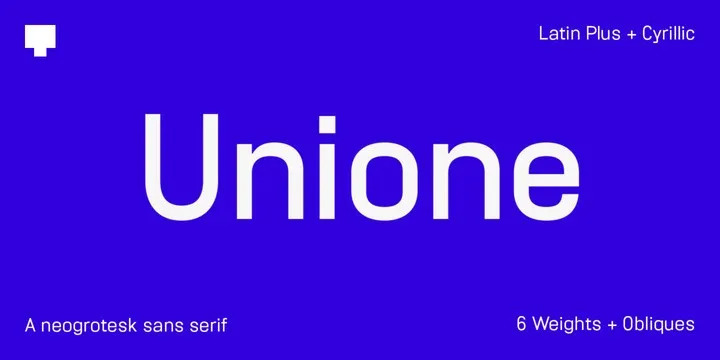
A Befonts está entusiasmada ao apresentar uma nova família de fontes sans-serif moderna. Esta é uma família de tipo sans serif universal – limpa e eterna, perfeita para um leque vasto de necessidades, desde identidades de marcas até design editorial, publicidade e logotipos. A Unione Font foi criada pelo designer TOMO Fonts e apresenta um estilo clean e moderno, com uma pegada geométrica. Esta família de fontes é disponível em seis pesos (agressivo e redondinho) e inclui suas respectivas obliques. Com mais de 28 membros na família, cada tipo possui mais de mil caracteres! Além disso, a Unione Font oferece uma ampla gama de suporte linguístico, incluindo o Latin Plus e Cyrillic. Os interessantes alternados estilísticos da Unione estão à disposição para você explorar.